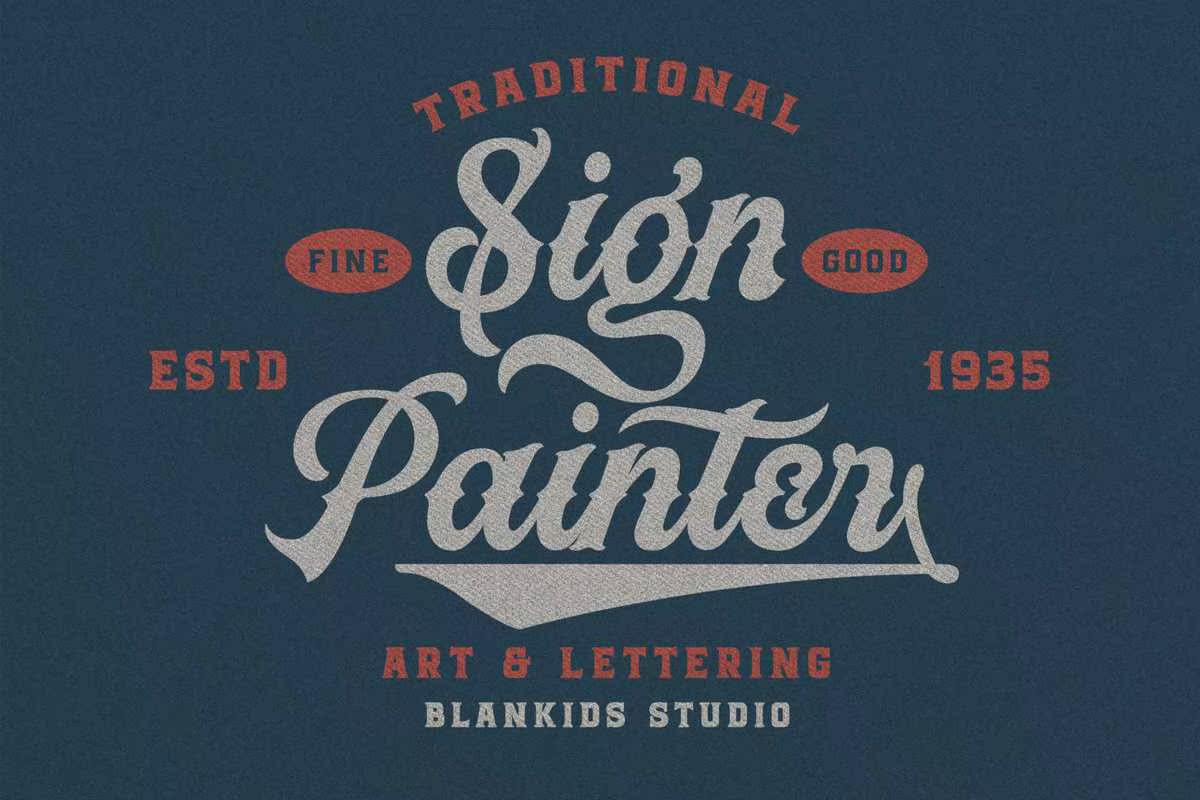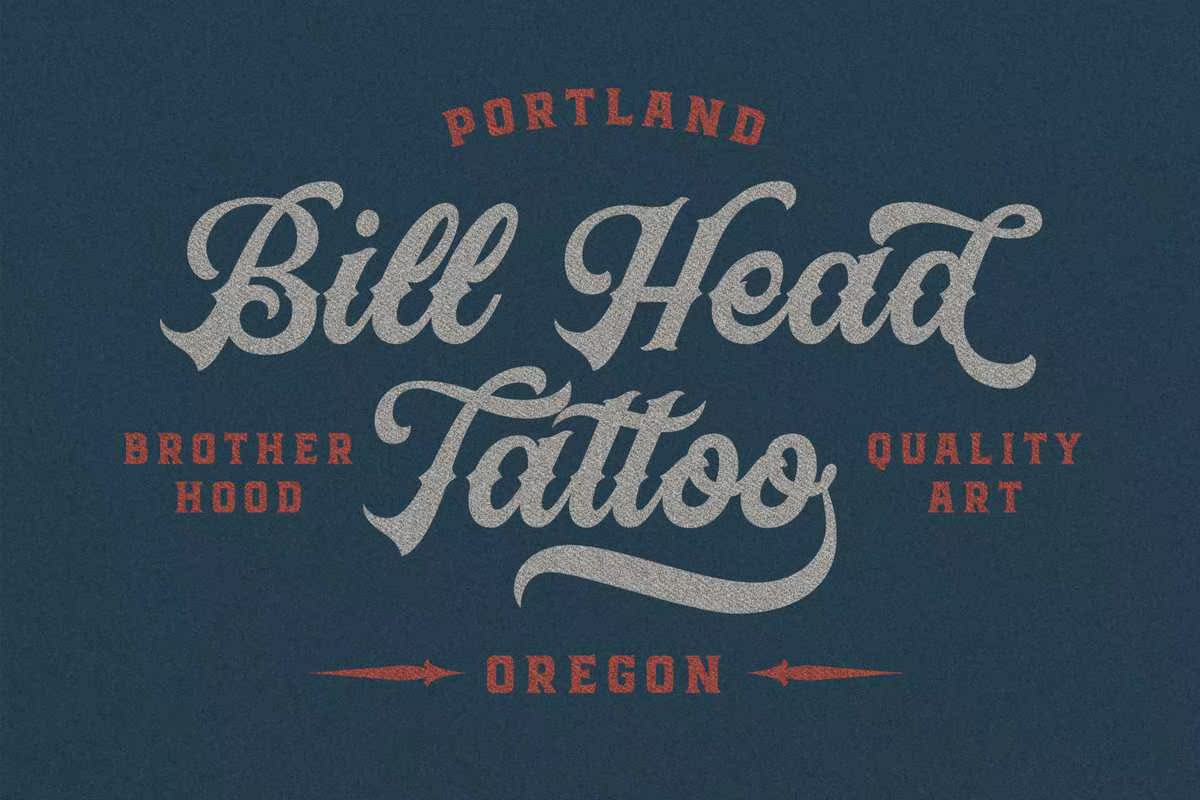
BlackJack带有2种风格的商标说明和黑体字,采用了恰当的组合字体,受古代海报、布袋、包装、标签上的商标风格的启发。BlackJack有400多个字体,具有多种风格的字符、交替字符、swash,Ligature and当然具有多语言支持。我还添加了右旋标签和徽章。BlackJack具有2种风格的商标说明和粗体系列完美的组合字体,ImadeblackJack受到海报、布袋、包装、标签上的商标风格的启发。BlackJack有400多个字体,具有多种风格的字符、交替字符、swash,当然,韧带和具有多语言支持。我还添加了右旋纤绳和徽章。